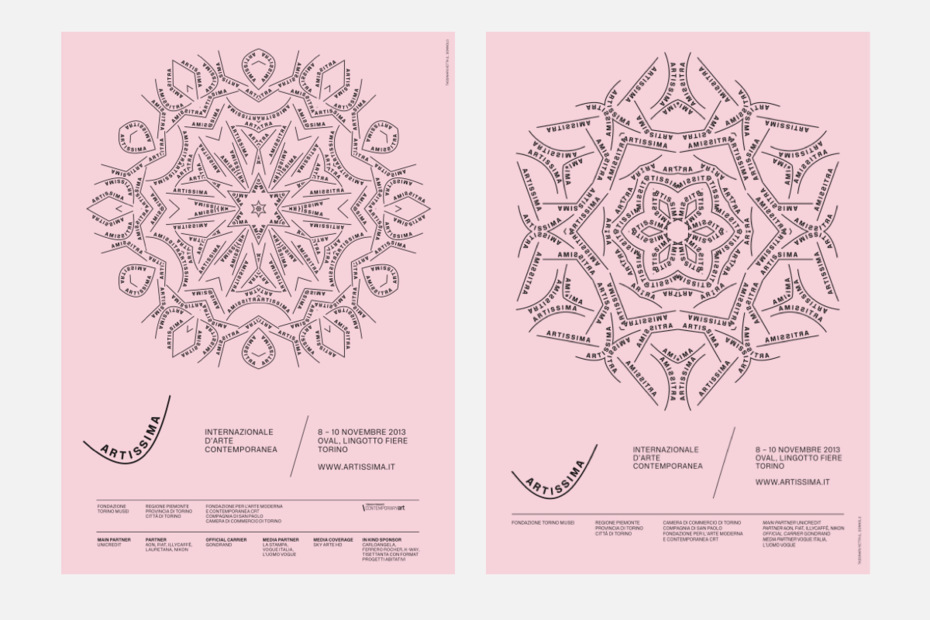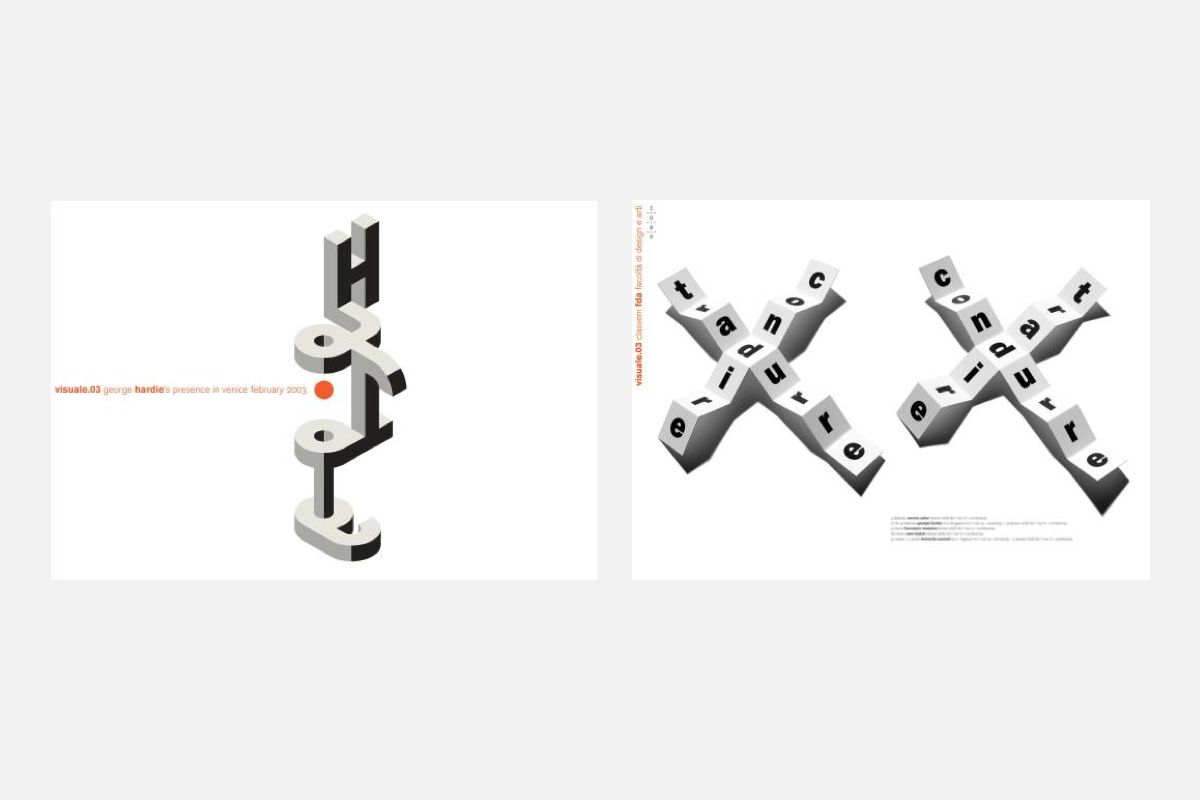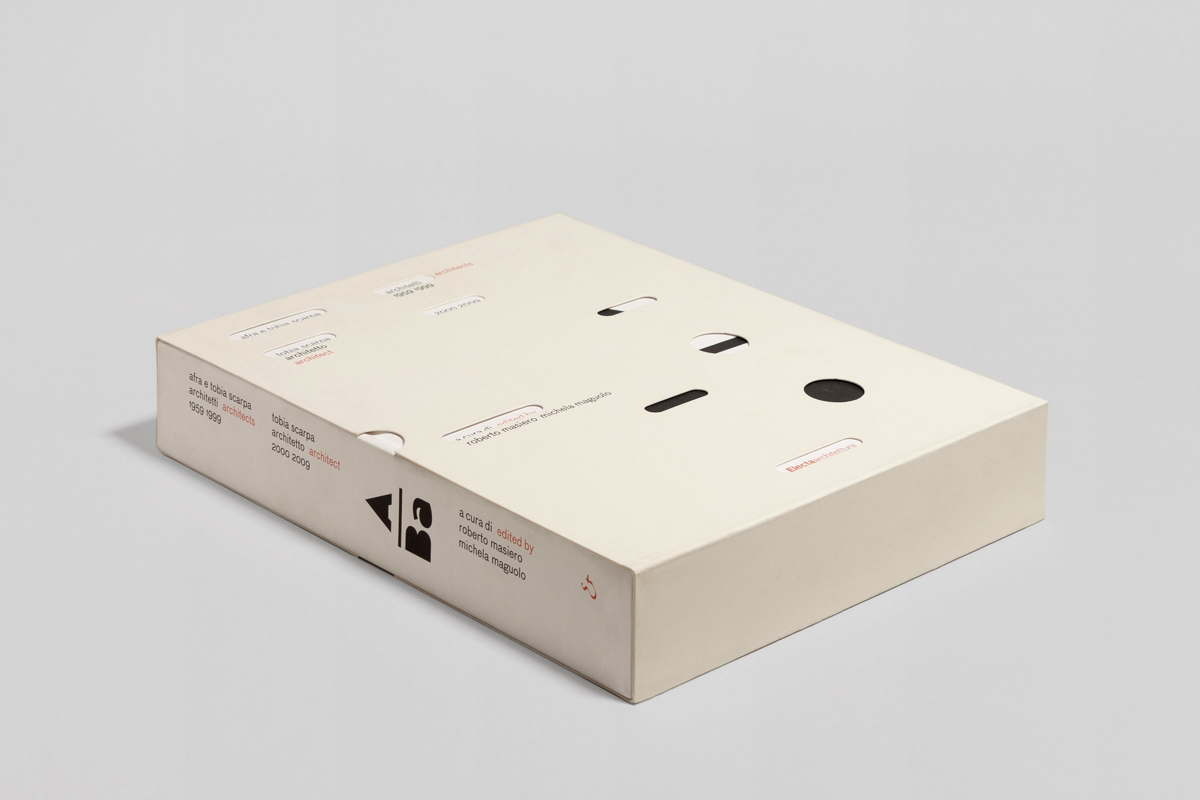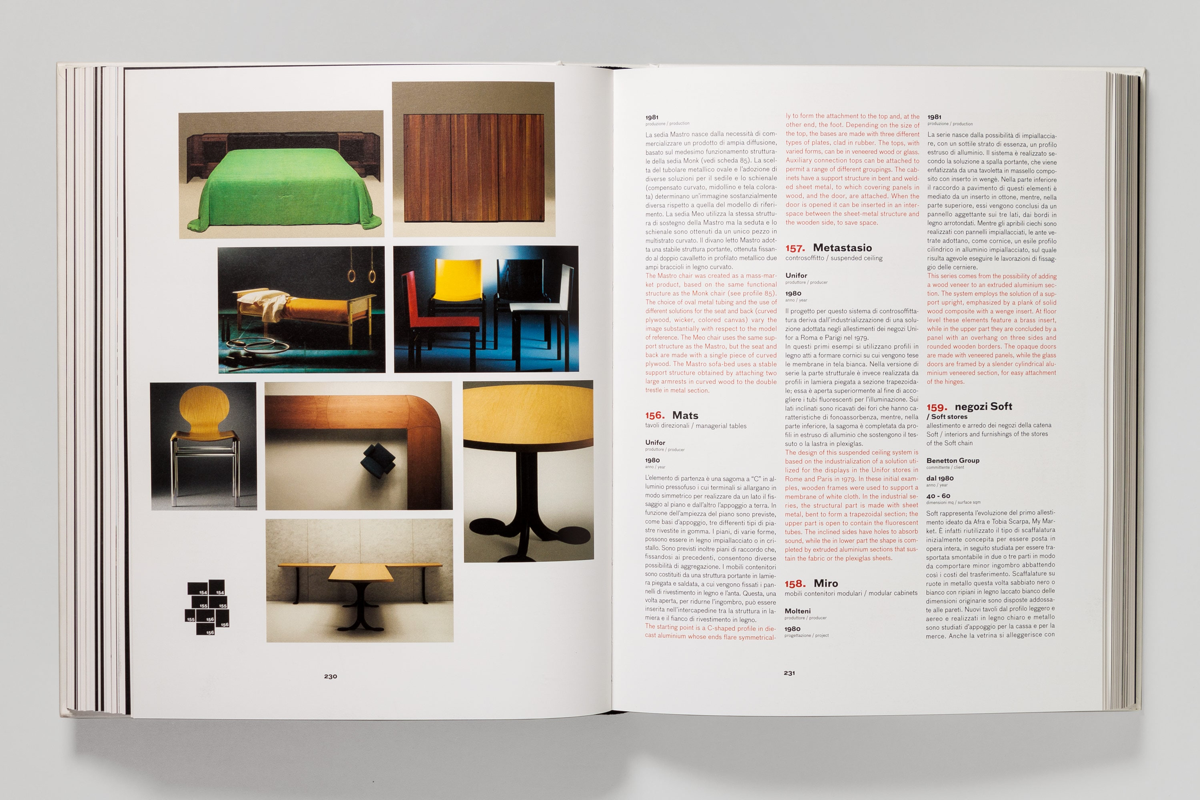
Интервью с Леонардо Сонноли
вон­кое имя Сон­но­ли я впер­вые узнал в 2004 го­ду из жур­на­ла [как), а имен­но из «Но­ме­ра про бук­вы», где бы­ла по­ме­ще­на ста­тья Сер­гея Се­ро­ва о нём вме­сте с де­сят­ком све­жих пла­ка­тов. По­сте­ры за­хва­ты­ва­ли: лет­те­ринг на­кла­ды­вал­ся на слож­ные трёхмер­ные сет­ки, бук­вы на­хо­ди­лись в край­не ди­на­мич­ных от­но­ше­ни­ях с про­стран­ством ли­ста. За­хва­ты­ва­ли, но, го­во­ря чест­но, бы­ли да­ле­ки от мо­е­го не­окреп­ше­го ума — боль­ше увле­ка­ло су­ма­сше­ствие, ко­то­рое тво­ри­лось в жур­на­ле на раз­во­ро­те ря­дом (там бы­ли де­таль­но по­ка­за­ны шриф­ты Фран­ти­ше­ка Штор­ма), и ми­ло­та на раз­во­ро­те по со­сед­ству (с щед­ро рас­сы­пан­ной кал­ли­гра­фи­ей Хол­ли Дик­кенс). В этом го­ду Сон­но­ли был го­стем «Ти­по­ма­нии», и его вы­ступ­ле­ние по­ка­за­лось мне од­ним из са­мых яр­ких на фе­сти­ва­ле. Что бы­ло не до кон­ца по­нят­но в 2004-м, ста­ло про­зрач­ным: в сво­их ра­бо­тах Сон­но­ли буд­то про­тя­ги­ва­ет ру­ки в раз­ные сто­ро­ны: од­ну он по­да­ёт клас­си­кам аван­гар­да и ди­зай­на, а вто­рую — со­вре­мен­ни­кам и но­вым тех­но­ло­ги­ям и тем са­мым вы­стра­и­ва­ет от­то­чен­ные, глу­бо­кие об­ра­зы. Бла­го­да­рим ор­га­ни­за­то­ров фе­сти­ва­ля за воз­мож­ность по­бе­се­до­вать с ди­зай­не­ром о вол­ну­ю­щих нас ве­щах. — Р. Г.
Лео­нар­до Сон­но­ли в го­стях у Алек­сан­дра Ла­врен­тье­ва (ис­кус­ство­ве­да, вну­ка Алек­сан­дра Род­чен­ко). Сон­но­ли ко­пи­ру­ет зна­ме­ни­тую фо­то­гра­фию Ма­я­ков­ско­го, сде­лан­ную Род­чен­ко в 1924 го­ду (стул тот са­мый!). Моск­ва, 2008, 2018.
Вар­ва­ра Гон­ча­ро­ва: Преж­де чем мы на­чнём го­во­рить о ди­зай­не, рас­ска­жи­те о том, что вас вдох­нов­ля­ет. Мо­жет быть, ли­те­ра­ту­ра, ки­но или му­зы­ка?
Не­про­стой во­прос. Мне ка­жет­ся, вдох­но­ве­ние при­хо­дит от куль­ту­ры во­об­ще. Сквозь приз­му куль­ту­ры я под­ме­чаю но­вые ве­щи или яв­ле­ния, ко­то­рые вос­хи­ща­ют ме­ня и ста­но­вят­ся ис­точ­ни­ком вдох­но­ве­ния. Я лю­блю ев­ро­пей­ский аван­гард. Сна­ча­ла это был аван­гард на­ча­ла XX ве­ка, рус­ский аван­гард, кон­струк­ти­визм, гол­ланд­ский аван­гард, Ба­у­ха­уз, за­тем ита­льян­ский фу­ту­ризм и дви­же­ние да­да в Гер­ма­нии.
Мне ин­те­рес­но, как аван­гард раз­ви­вал­ся, осо­бен­но по­сле пе­ре­ры­ва, вы­зван­но­го Вто­рой ми­ро­вой вой­ной, и его пе­ре­ро­жде­ние по­сле 30-х и 40-х го­дов в нео­аван­гард. Ме­ня увле­ка­ют ви­зу­аль­ная по­э­зия и кон­цеп­ту­а­лизм, по­то­му что в их осно­ве ле­жит идея, и ху­дож­ник на­чи­на­ет ра­бо­тать со сло­ва­ми, с язы­ком и ви­зу­аль­ной по­э­зи­ей как та­ко­вой. Мне все­гда бы­ло ин­те­рес­но со­зда­вать что-то при по­мо­щи слов, букв, по­это­му ме­ня вдох­нов­ля­ют все ху­до­же­ствен­ные те­че­ния, ко­то­рые ис­поль­зу­ют бук­вы и язык.
Ча­сто ис­кус­ство и ди­зайн пе­ре­се­ка­ют­ся, од­но ссы­ла­ет­ся на дру­гое, дви­же­ние аван­гар­да, кон­струк­ти­визм, фу­ту­ризм ис­сле­ду­ют ди­зайн, и на­о­бо­рот. Я ду­маю, что, со­зда­вая гра­ни­цы меж­ду дис­ци­пли­на­ми в ис­сле­до­ва­тель­ских це­лях, мы долж­ны не за­бы­вать о кон­тек­сте, ко­то­рый вли­ял на них.
Ве­ра Кар­за­ко­ва: Вас вдох­нов­ля­ет ис­то­рия ис­кусств, а как на­счёт по­ли­ти­че­ских со­бы­тий?
Я ре­а­ги­рую на по­ли­ти­ку в пер­вую оче­редь как гра­жда­нин, а как ди­зай­нер го­раз­до мень­ше. В про­фес­си­о­наль­ной жиз­ни, у се­бя в офи­се, я не ощу­щаю пря­мо­го вли­я­ния по­ли­ти­че­ских со­бы­тий. Ста­ра­юсь раз­де­лять эти сфе­ры — я как че­ло­век и гра­жда­нин и я как ди­зай­нер. Ча­сто спра­ши­ваю се­бя: а что, если по­ли­ти­че­ская пар­тия, ко­то­рая мне не нра­вит­ся, по­про­сит ме­ня что-то сде­лать для них? С од­ной сто­ро­ны, я не хо­чу по­мо­гать тем, кто мне не нра­вит­ся, не хо­чу по­вы­шать их вли­я­ние. Но, с дру­гой сто­ро­ны, я про­фес­си­о­нал, и если кли­ент про­сит ме­ня сде­лать ра­бо­ту, то я дол­жен сде­лать её на­столь­ко хо­ро­шо, на­сколь­ко смо­гу. Тут нет од­но­знач­но­го от­ве­та. Ино­гда, ко­гда я пре­по­даю, то об­су­ждаю со сту­ден­та­ми по­ли­ти­че­ские во­про­сы, но ча­ще все­го это про­сто шут­ки.
Вар­я: Мы в помещении с плакатами, ко­то­рые при­ве­зе­ны сю­да со все­го ми­ра. Ка­жет­ся, этот жанр чув­ству­ет се­бя хо­ро­шо и не со­би­ра­ет­ся ис­че­зать.
Да, по­то­му что пла­кат — это всё ещё ин­стру­мент.
Ва­ря: Но го­во­рят, что ско­ро пла­ка­ты как жанр ис­чез­нут пол­но­стью. Что ду­ма­е­те вы? Есть ли у пла­ка­тов серьёз­ная функ­ция се­го­дня, или ди­зай­не­ры де­ла­ют их ра­ди удо­воль­ствия?
В ва­шем во­про­се со­дер­жит­ся и от­вет. Мно­гие ди­зай­не­ры де­ла­ют пла­ка­ты для удо­воль­ствия. Я ду­маю, что это од­на из воз­мож­ных форм, с по­мо­щью ко­то­рых ди­зай­нер мо­жет вза­и­мо­дей­ство­вать со зри­те­лем. Вре­ме­на­ми это очень силь­ный ин­стру­мент для ком­му­ни­ка­ции, а ино­гда — сла­бый и бес­по­лез­ный. Вы бы­ва­ли в Ве­не­ции?
Вар­ва­ра и Ве­ра: Нет.
Ве­не­ция — ма­лень­кий го­род, в нём нет ав­то­мо­биль­ных улиц, толь­ко лод­ки. При­хо­дит­ся мно­го хо­дить пеш­ком, и по­это­му от­но­ше­ния, ко­то­рые у вас ск­ла­ды­ва­ют­ся с про­стран­ством и вре­ме­нем в Ве­не­ции, со­вер­шен­но от­ли­ча­ют­ся от мо­сков­ских, на­при­мер. В Ве­не­ции уз­кие ули­цы, так что, если я по­ве­шу пла­кат, у лю­дей, ко­то­рые прой­дут ми­мо, бу­дет до­ста­точ­но вре­ме­ни и про­стран­ства, что­бы раз­гля­деть и про­чи­тать его. Если же я по­ве­шу пла­кат в Моск­ве, то его ни­кто не уви­дит. Здесь нет про­странств для пла­ка­тов, толь­ко для огром­ных бил­бор­дов. Раз­ве что на Ар­ба­те, где про­гу­ли­ва­ют­ся лю­ди, мы мо­жем пред­ста­вить се­бе не­сколь­ко по­сте­ров, но толь­ко не на сте­нах, а где-то пря­мо по­сре­ди ули­цы.
Я ду­маю, что бес­смыс­лен­но со­зда­вать пла­кат про вы­став­ку в Тре­тья­ков­ской га­ле­рее, на­при­мер. Тут при­го­дит­ся ин­тер­нет-ре­кла­ма, бил­борд, оформ­лен­ный ав­то­бус. Или мож­но рас­кла­ды­вать по­что­вые от­крыт­ки с ре­кла­мой вы­став­ки по ба­рам. Од­ним сло­вом, вы­бор ин­стру­мен­та для ком­му­ни­ка­ции — важ­ный шаг для ди­зай­не­ра.
Ве­ра: Вы участ­ву­е­те в кон­кур­сах пла­ка­тов?
Я по­лу­чаю мно­же­ство при­гла­ше­ний, но обыч­но не участ­вую. Знаю на­вер­ня­ка, что мой пла­кат бу­дет на­пе­ча­тан циф­ро­вым спо­со­бом и ча­сто не в са­мом хо­ро­шем ка­че­стве. К то­му же, если я сде­лаю по­стер про­тив пла­сти­ко­вых бу­тыл­ок или за, его по­ве­сят в га­ле­рее, и толь­ко гра­фи­че­ские ди­зай­не­ры его уви­дят, но не те лю­ди, ко­то­рые поль­зу­ют­ся пла­сти­ко­вы­ми бу­тыл­ка­ми. То есть я про­сто по­ка­жу дру­гим ди­зай­не­рам, ка­кой я хо­ро­ший пла­ка­тист. Пе­чаль­но, что эти кон­кур­сы не об эко­ло­гии и не о сво­бо­де сло­ва — они о гра­фи­че­ском ди­зай­не.
Ва­ря: Рас­ска­жи­те, по­жа­луй­ста, о книж­ных фе­сти­ва­лях или вы­став­ках в Ита­лии.
Я бы от­ме­тил фе­сти­валь Fahrenheit39, ко­то­рый ор­га­ни­зу­ет еже­год­но мой быв­ший сту­дент, и яр­мар­ку дет­ской ли­те­ра­ту­ры в Бо­ло­нье. Она не со­всем про ди­зайн, но име­ет очень боль­шое зна­че­ние.